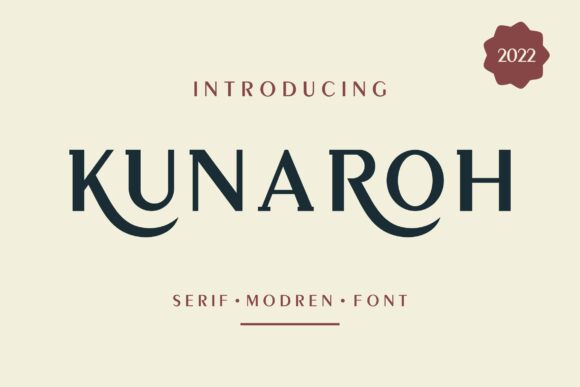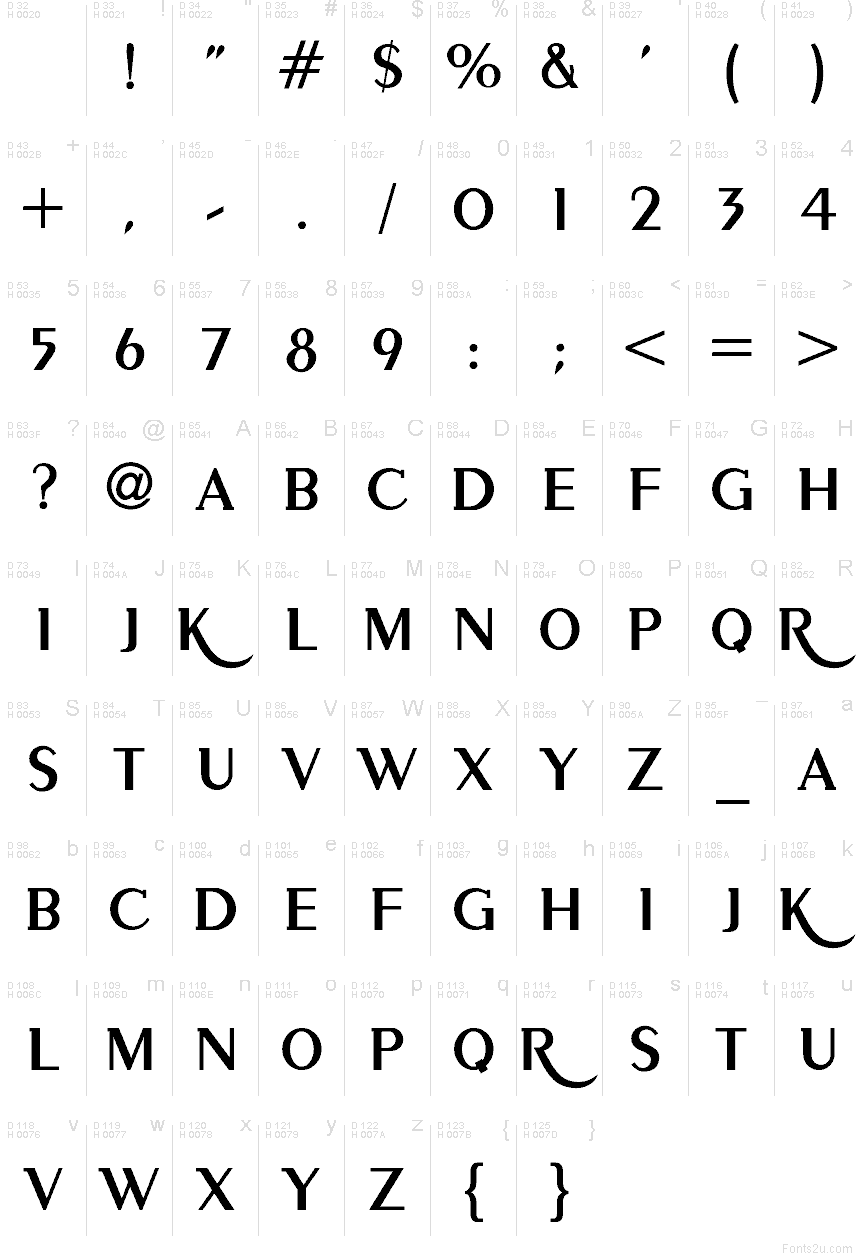
Kunaroh von Albert Kalingga ist eine kostenlose Versalschrift für Displays, die mit einem kalligrafischen Serifendesign und hohem Kontrast besticht. Die Buchstaben wirken hoch und zeremoniell; sie kombinieren scharfe vertikale Formen mit schwungvollen Kurven, die in langen, eleganten Ausläufen enden. Dies verleiht der Schrift einen raffinierten Rhythmus mit einer leicht theatralischen Note.
Sie eignet sich hervorragend für Branding, Buchcover, Mode-Überschriften, Plakat-Titel und Monogramme, bei denen die verlängerten Striche visuell für sich stehen können. Als kostenlose Schrift entfaltet Kunaroh ihre Wirkung am besten in kurzen Zeilen und Initialen – ideal, wenn ein Titel oder ein Schriftzug formell, stilvoll und mit einer Spur Dramatik gestaltet werden soll.